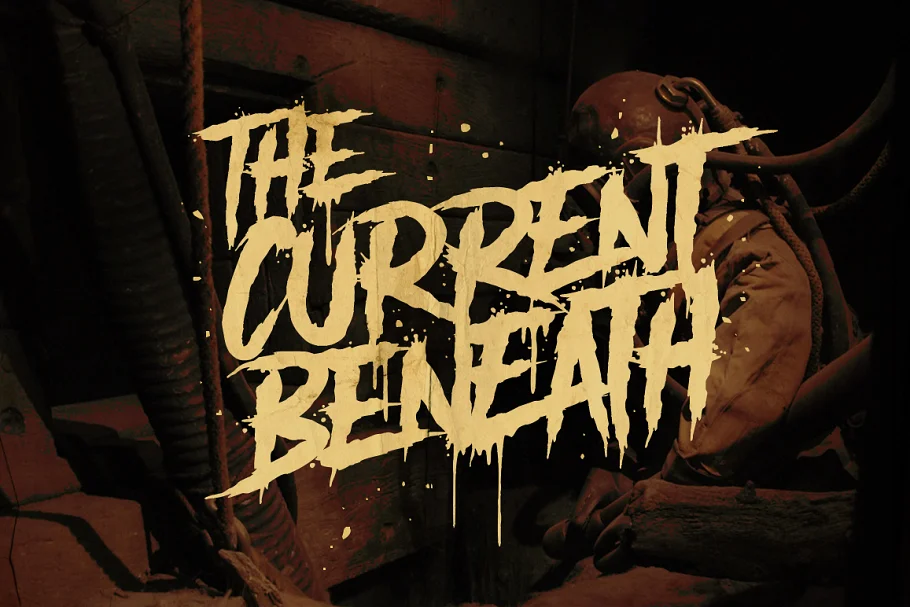
Another Danger Font
Description de Another Danger Font
Présentation de Another Danger, la police d’horreur qui défie les conventions et embrasse le chaos à chaque trait. Né d’encres indisciplinées qui confèrent à chaque glyphe une allure énigmatique, Another Danger est plus qu’une simple police, c’est une déclaration, une rébellion contre le banal.
Qu’il s’agisse d’une affiche, d’un album ou d’une marque, Another Danger est votre cache secrète. Répandez votre créativité sur tout le papier, aussi ordinaire ou abstrait soit-il. Lorsqu’Another Danger est en jeu, les opportunités sont innombrables et le danger peut être caché comme s’il était en dessous.
1. Que signifie Another Danger Typeface ?
En revanche, Danger se démarque des autres polices par son exubérance de lettres illisibles. Cela va au-delà de la norme des polices précédentes : elle accueille les imperfections, chaque glyphe ayant un air d’imprévisibilité et chaque étincelle d’excitation. La nervosité s’accompagne d’une ambiance industrielle hardcore et d’un style rétro qui complètent parfaitement n’importe quel design.
2. Par quels moyens puis-je intégrer la police Another Danger dans ma conception ?
Comparaison des polices Une autre police Danger peut être utilisée en composition dans différents contextes de conception. Il est particulièrement adapté aux projets où un design mortel, plein d’esprit et d’horreur est nécessaire, comme les affiches d’Halloween, les pochettes d’album, les campagnes de marque, etc. Explorez l’utilisation de différentes tailles, couleurs et effets de superposition pour obtenir un impact maximal.
3. La police Another Danger est-elle adaptée aux médias numériques ?
Bien entendu, la police Another Danger peut être utilisée dans les médias numériques tels que les sites, les graphiques de réseaux sociaux et les publicités numériques. Son style unique donne du caractère au projet et en fait une pièce facilement reconnaissable et enregistrée dans le subconscient de ses spectateurs potentiels.
4. La police Another Danger est-elle disponible avec différents styles ou graisses ?
Une autre police Danger se présente généralement dans un style, caractérisé par son apparence audacieuse et chaotique. Cependant, certaines variantes ou versions alternatives peuvent exister, offrant de légères modifications au design original. Assurez-vous d’explorer toutes les options supplémentaires disponibles lors de l’obtention de la police.